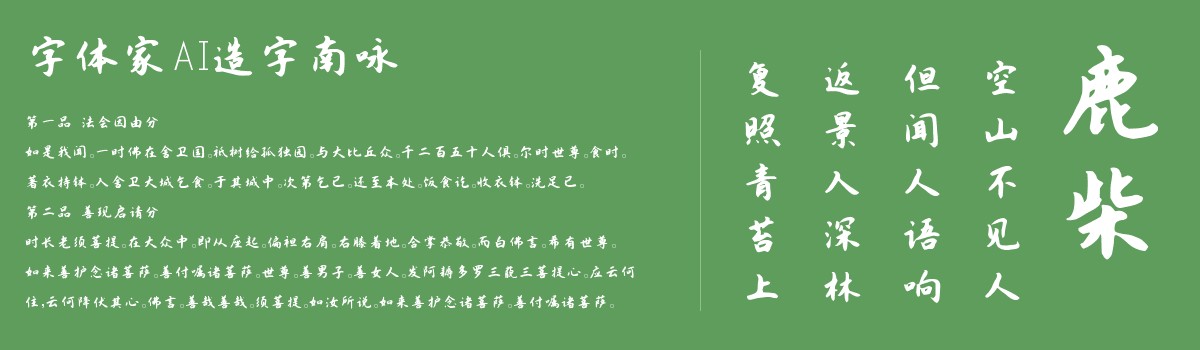
字体家AI造字南咏
字体家AI造字南咏是一款由字体家AI神笔造字生成的一款艺术字体,笔画流畅如行云,起笔轻顿似指尖触纸,收笔舒展若微风拂柳,转折圆润无棱角。线条粗细自然过渡,不刻意均匀却显手写从容。整体温润如玉,有书写灵动生气,又含沉静书卷韵,仿佛能触到笔尖在纸上缓缓游走的细腻轨迹。比较适合用于艺术类装饰文字,海报、网页、广告设计,室内装饰,平面标题设计、食品包装、品牌标志等。